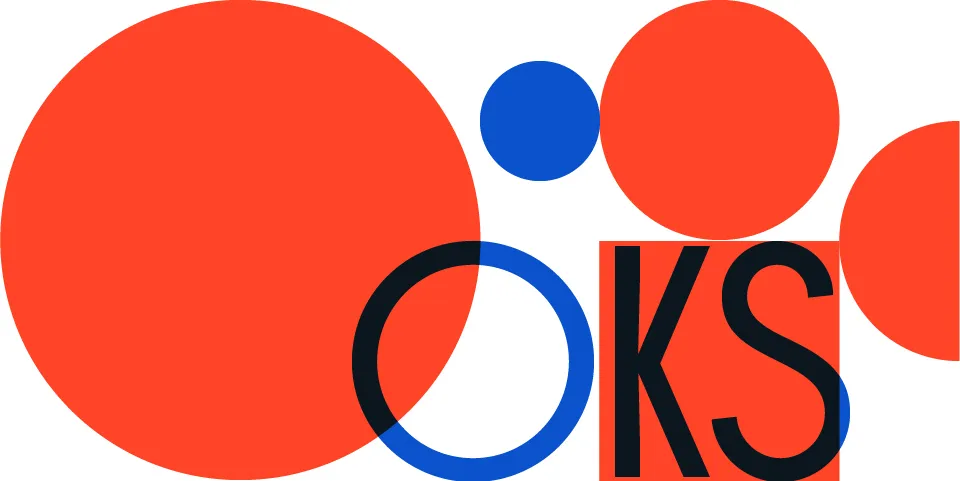
A fonte Oks é uma opção elegante para designers e impressões profissionais, especialmente na categoria sans serif. Ela foi compartilhada por Ilya Zherikov no Behance e seu estilo clean e moderno se destaca como alternativa a outros tipos sem serif que você pode encontrar em plataformas como Befonts. A fonte Oks é perfeitamente adequada para uso em projetos de design, seja em torno de textos informativos ou graficos visuais complexos. Suas linhas leves e suas facilidades de legibilidade fazem dela uma escolha segura para qualquer aplicação onde a simplicidade e o equilíbrio são valorizados. Se você está procurando por fontes sem serif que se destacam tanto quanto a Oks, Befonts é um ótimo lugar para explorar outros tipos similares, especialmente na seção sans serif.